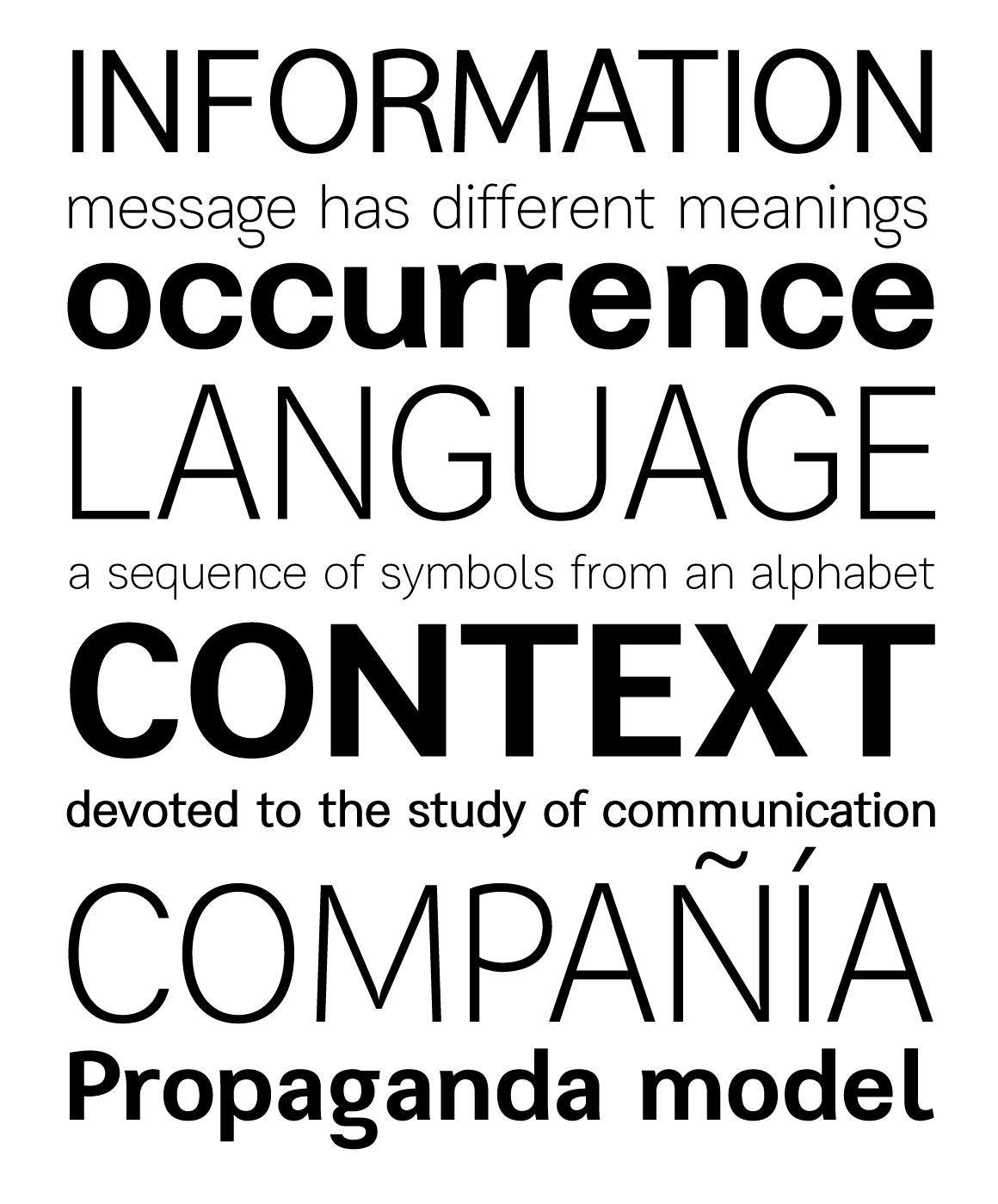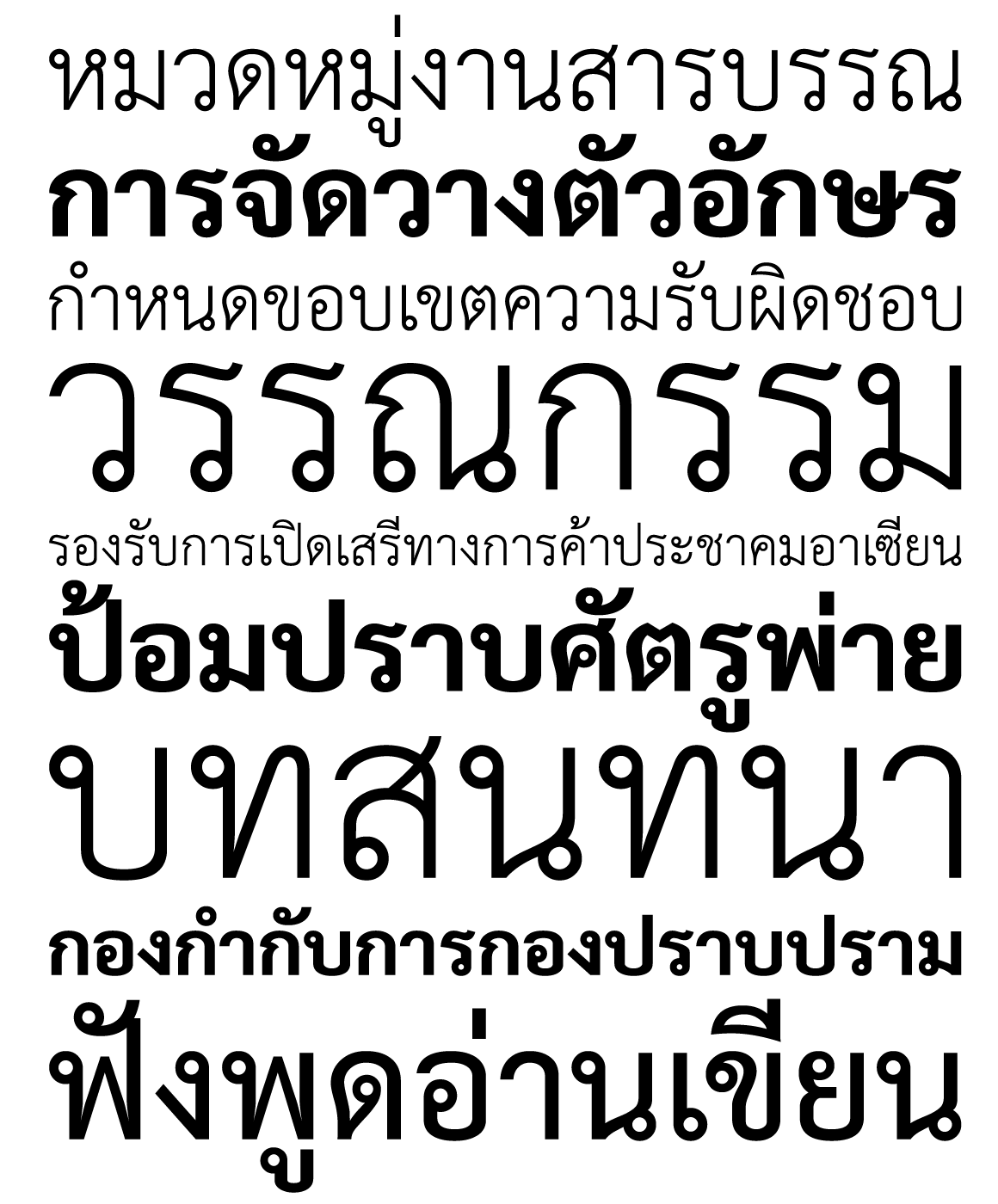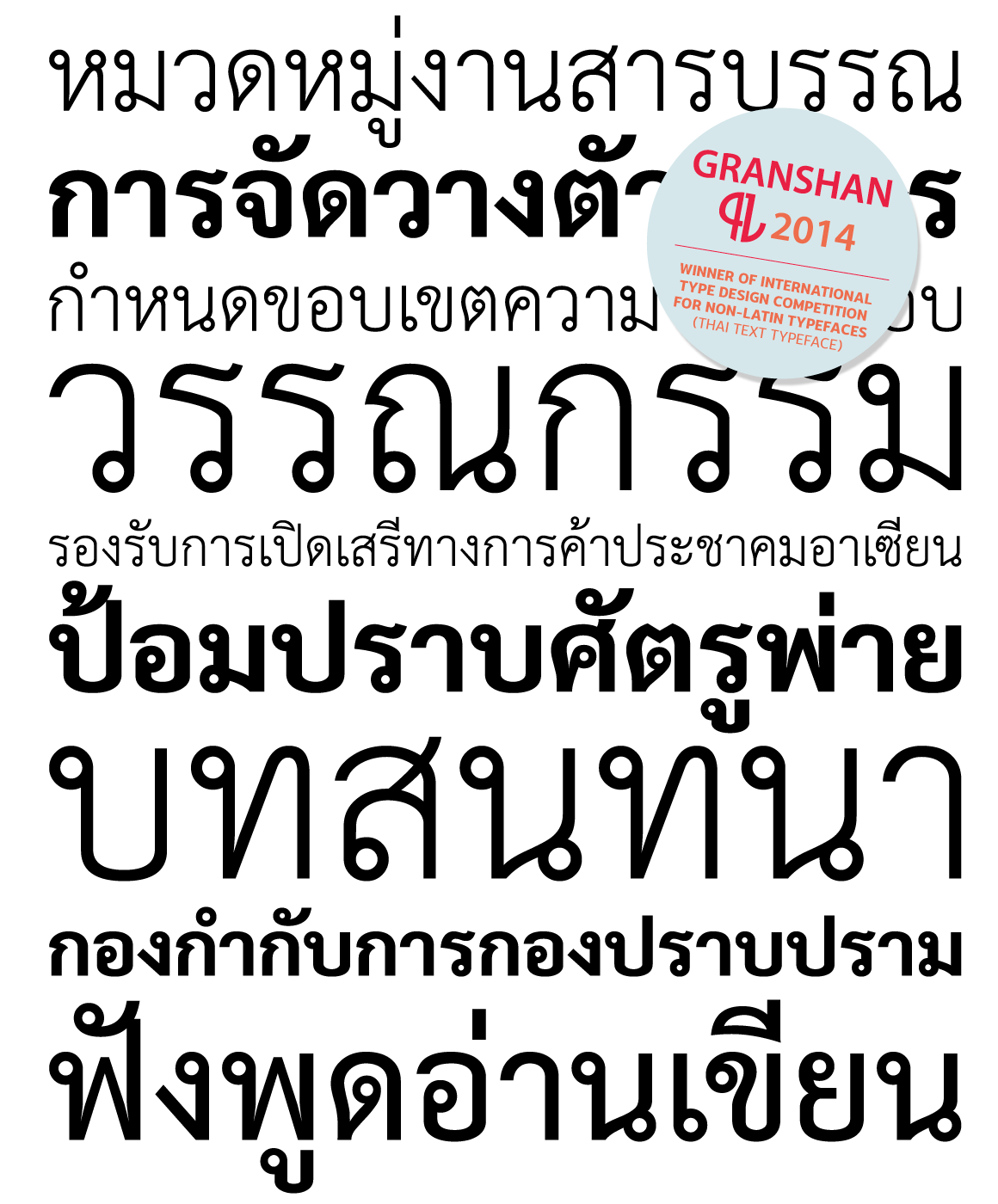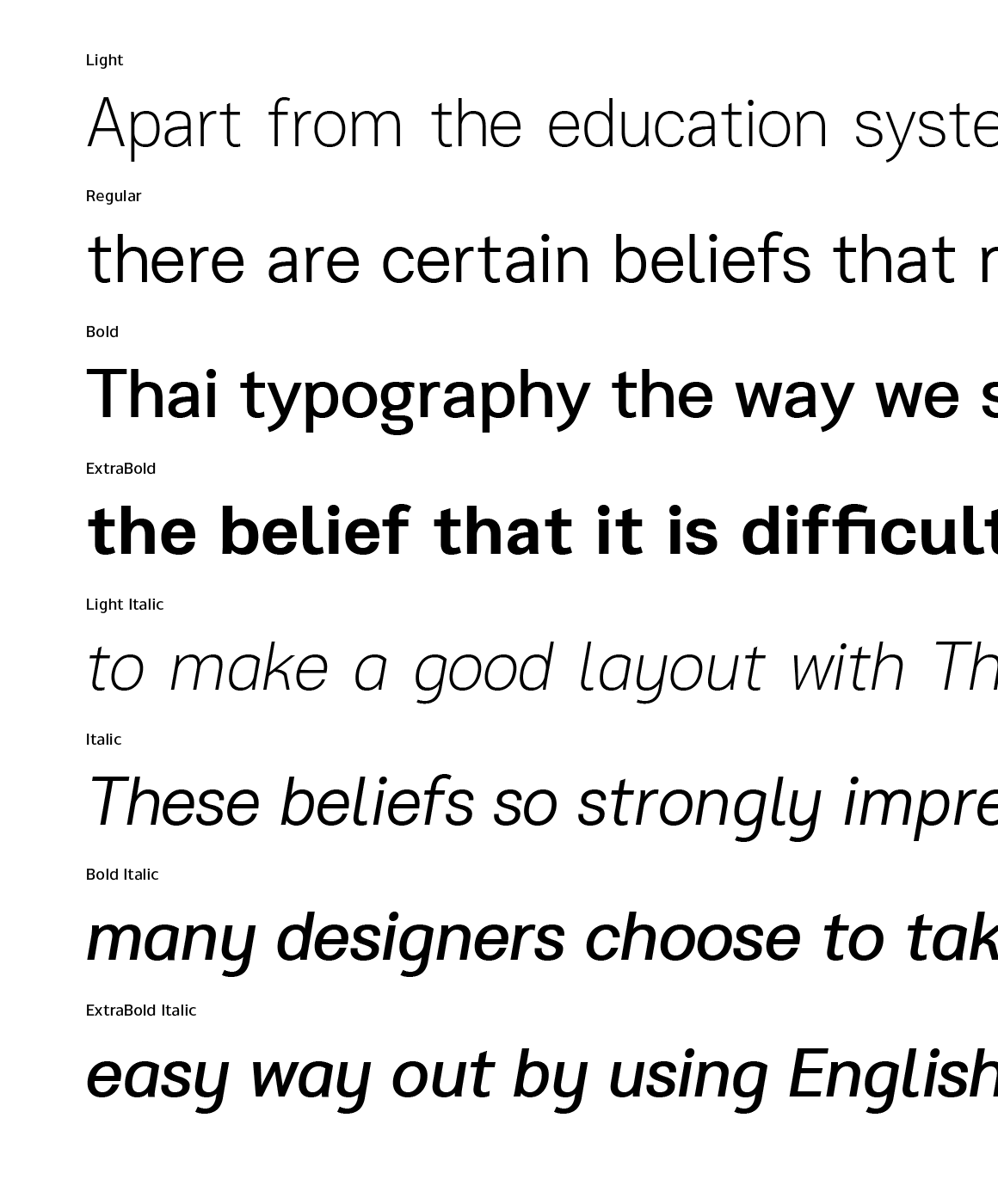
Sarabun Mai
จากแบบตัวพิมพ์ราชการที่ถูกใช้งานมากที่สุดสู่ชุดตัวอักษร “สารบรรณใหม่” ที่ขยายขอบเขตของน้ำหนักและปรับโครงสร้างใหม่ทั้งหมดเพื่อตอบสนองรองรับงานสิ่งพิมพ์และสื่อดิจิตอล รวมไปถึงขยายฐานของภาษาต่างๆ ให้ครอบคลุมการใช้งานได้มากยิ่งขึ้น นอกจากนี้ สารบรรณใหม่ ยังได้รับรางวัลการันตีจากเวทีการประกวดตัวอักษรระดับโลกอย่าง Grashan ในหมวด Non-Latin ประจำปี 2014 อีกด้วย
Name :Sarabun Mai
Weight : Light, Light Italic, Regular, Italic, Bold, Bold Italic, ExtraBold and ExtraBold Italic
Language : Latin 1 / Latin 2 / Vietnamese / Thai
Release Date : 2014
Designer : Suppakit Chalermlarp
Technician : Suppakit Chalermlarp
Award : Granshan Type Design Competition 2014